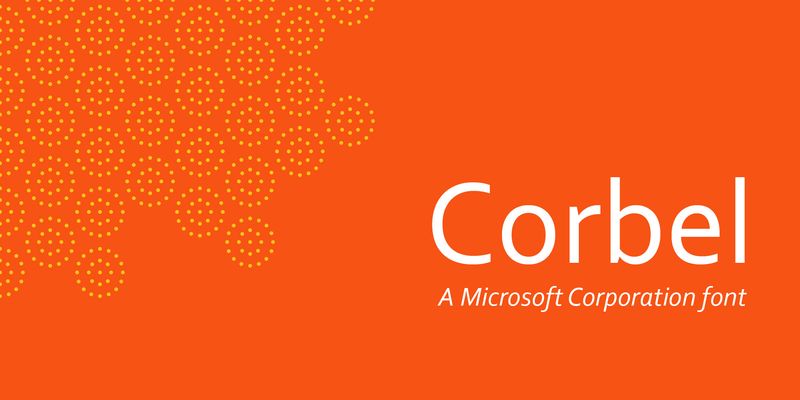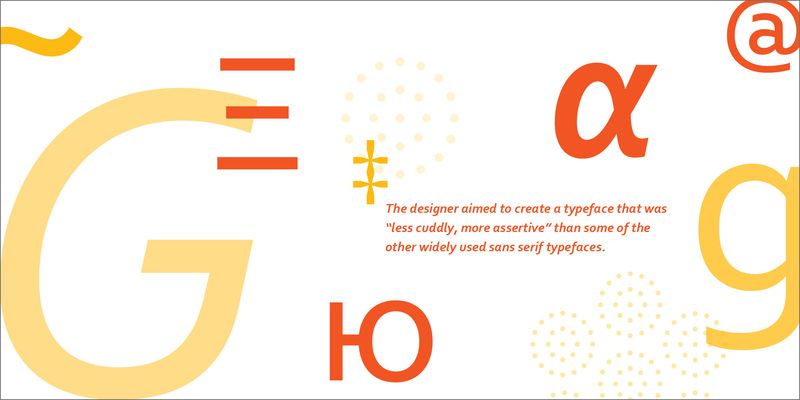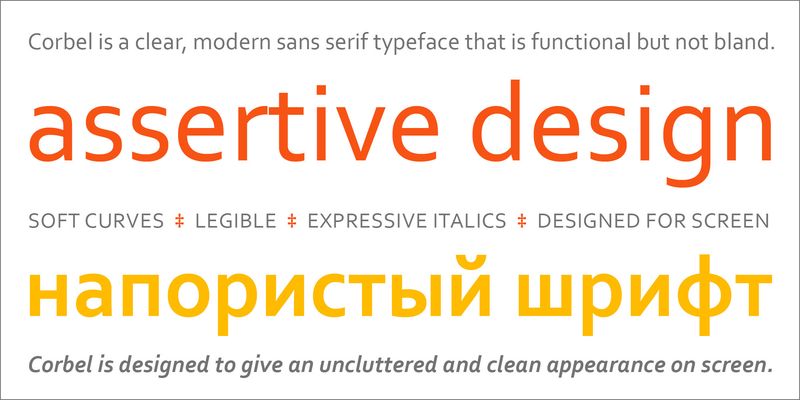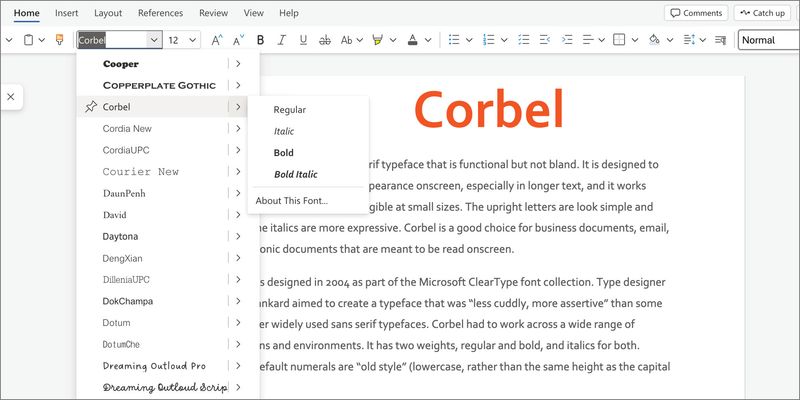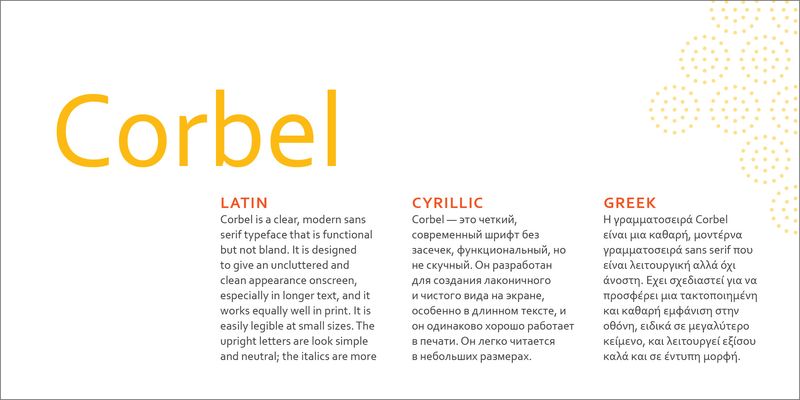
Corbel è un font sans serif chiaro e moderno, funzionale ma non insipido. È stato progettato per dare un aspetto ordinato e pulito sullo schermo, soprattutto nei testi più lunghi, e funziona altrettanto bene in stampa. È facilmente leggibile anche in piccole dimensioni. Le lettere verticali hanno un aspetto semplice e neutro, mentre il corsivo è più espressivo. Corbel è una buona scelta per i documenti aziendali, le e-mail e i documenti elettronici destinati a essere letti sullo schermo.
Corbel è stato progettato nel 2004 come parte della raccolta di font ClearType Microsoft. Il type designer Jeremy Tankard mirava a creare un font che fosse “meno coccoloso e più assertivo” rispetto ad alcuni degli altri font sans serif ampiamente utilizzati. Corbel doveva funzionare in un’ampia gamma di applicazioni e ambienti. Ha due spessori, regular e bold, e corsivo per entrambi. I numeri predefiniti di Corbel sono “vecchio stile” (minuscoli, anziché della stessa altezza delle lettere maiuscole).